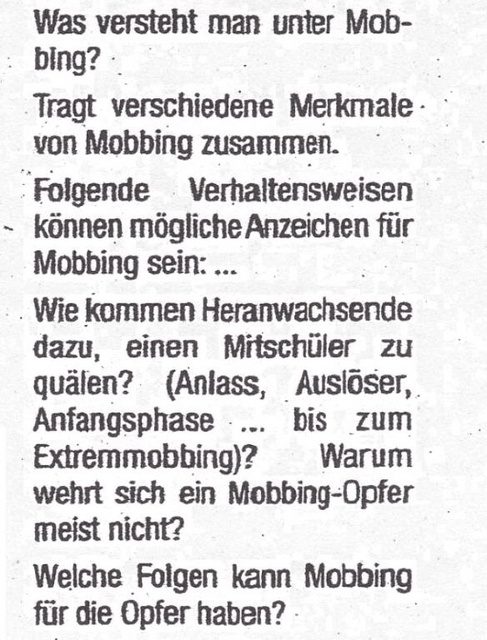
Schriftart der Mobbing-Fragen
Schönen guten Tag, suche die SChriftart dieser Fragen. Es ist nicht Arial - die SChrifthöhe ist höher als die von Arial - bitte um Mithilfe - habe auch schon die Fontdatenbank des Systems durchforstet, jedoch keine perfekte Übereinstimmung. Mit herzlichen Dank im Voraus.